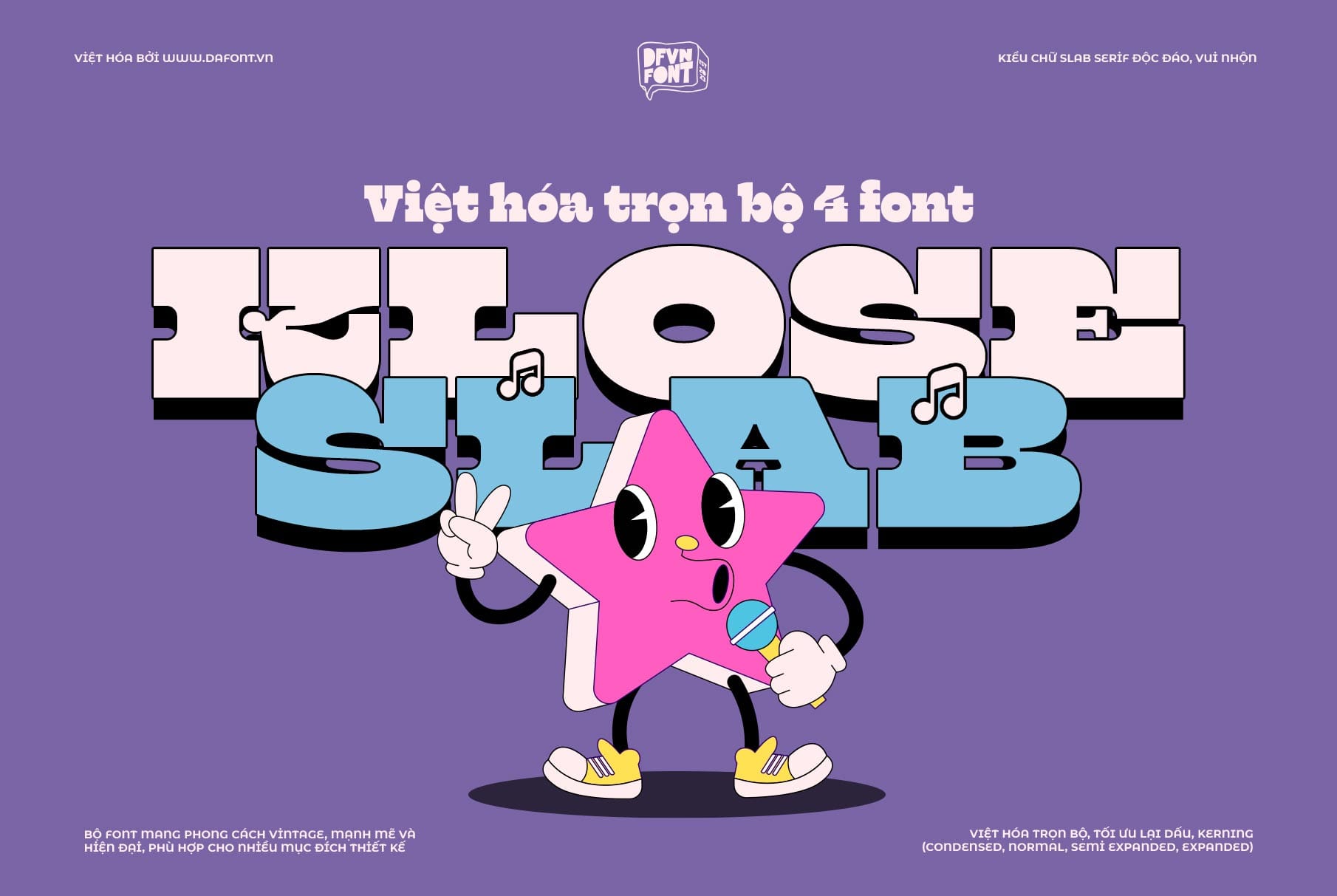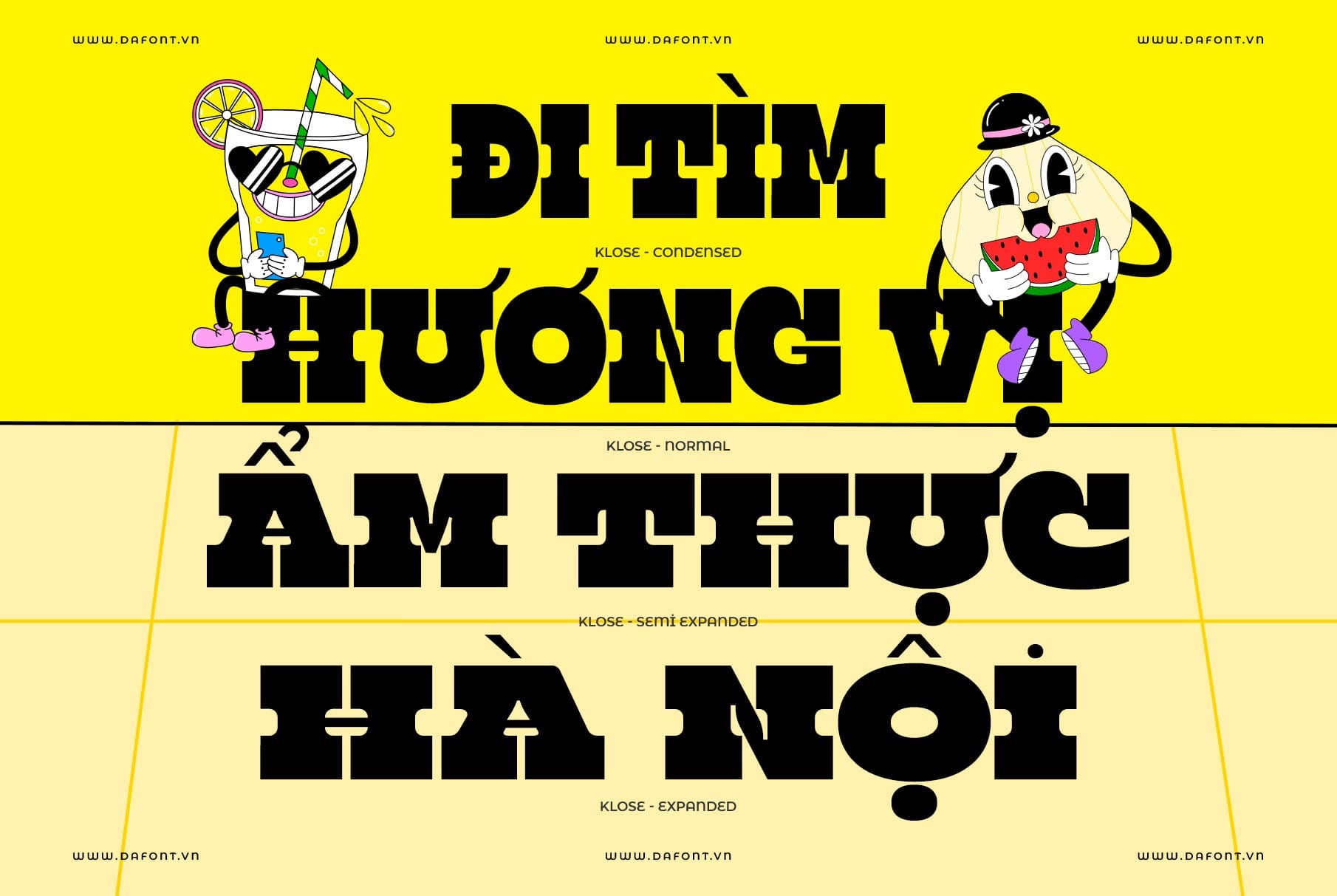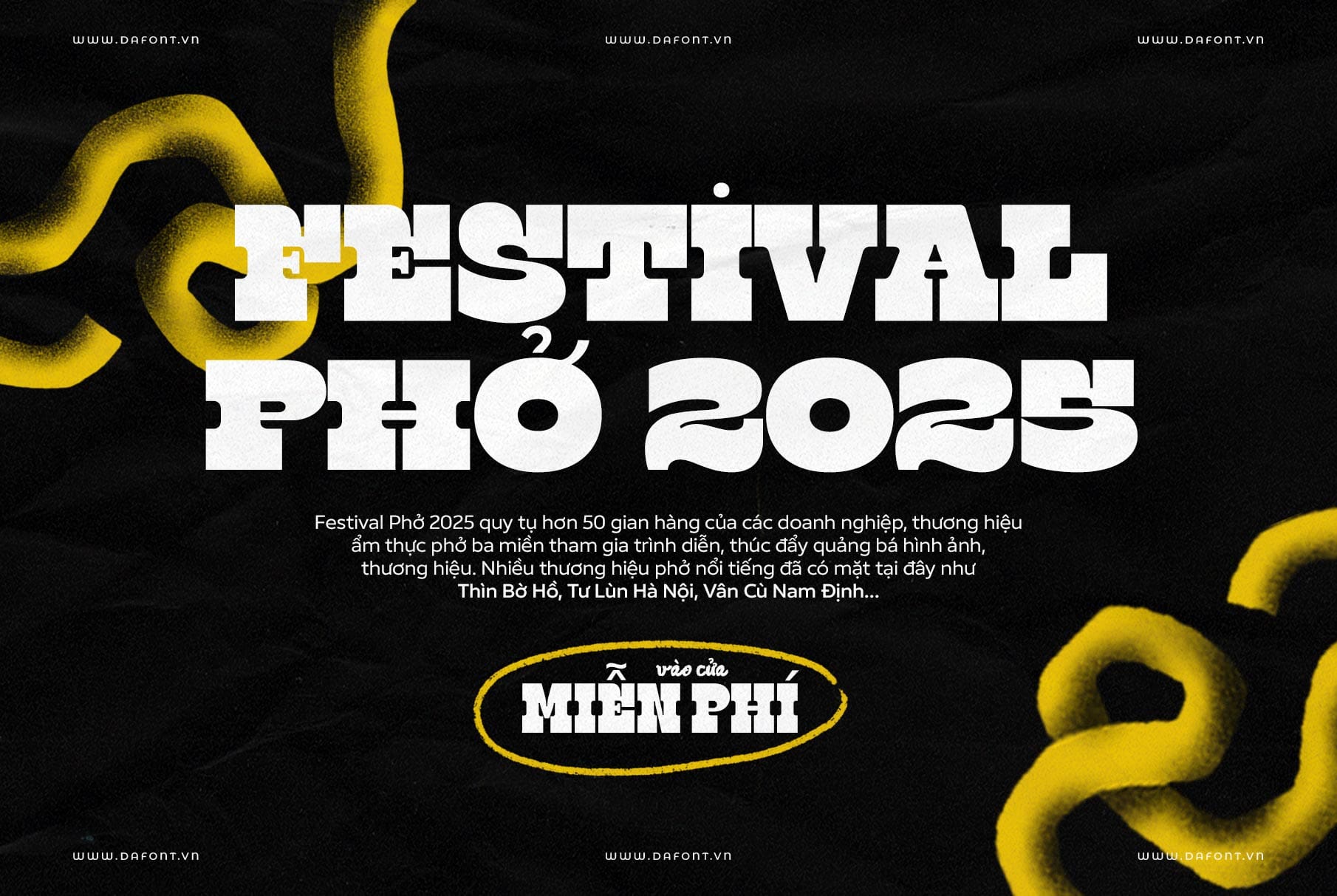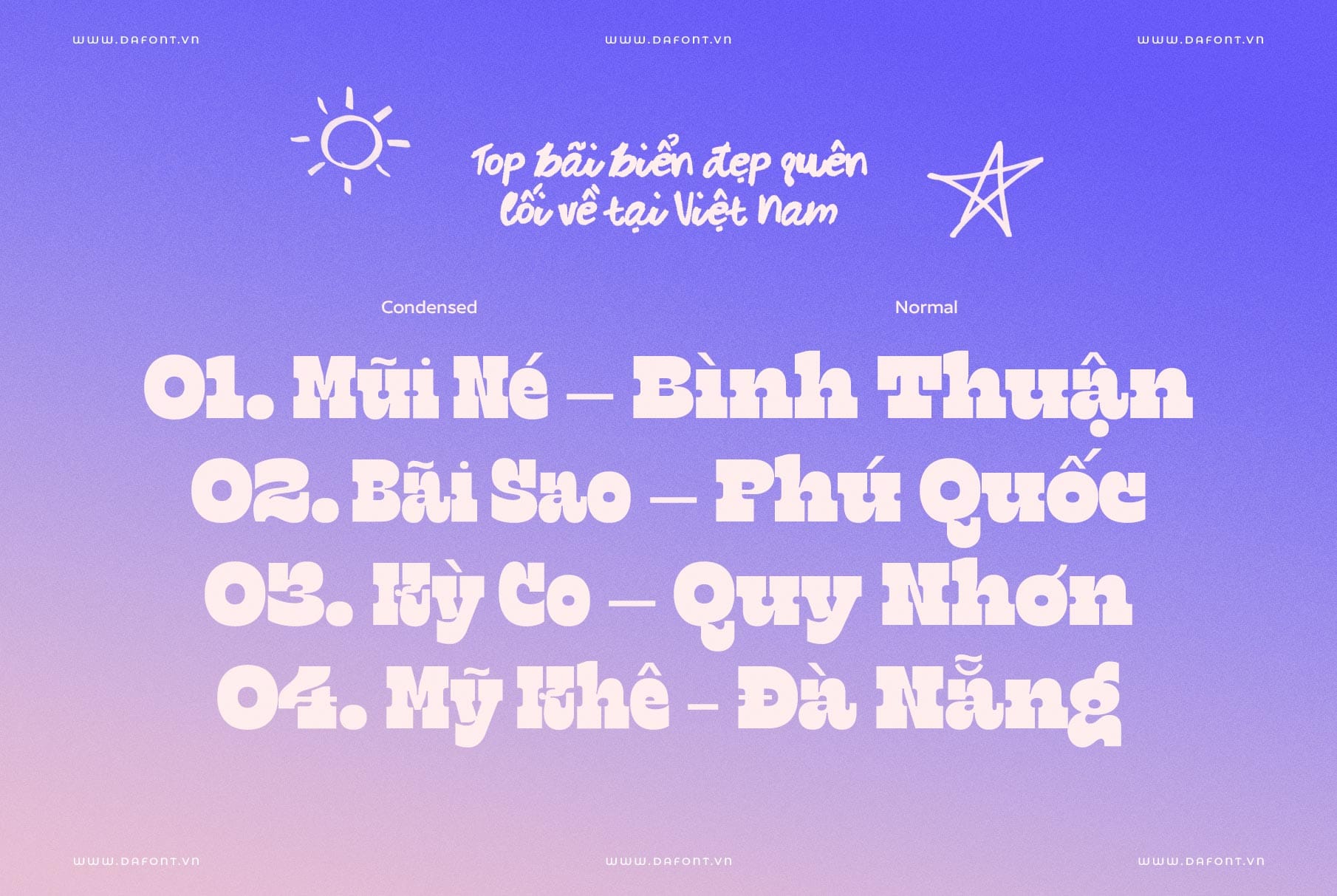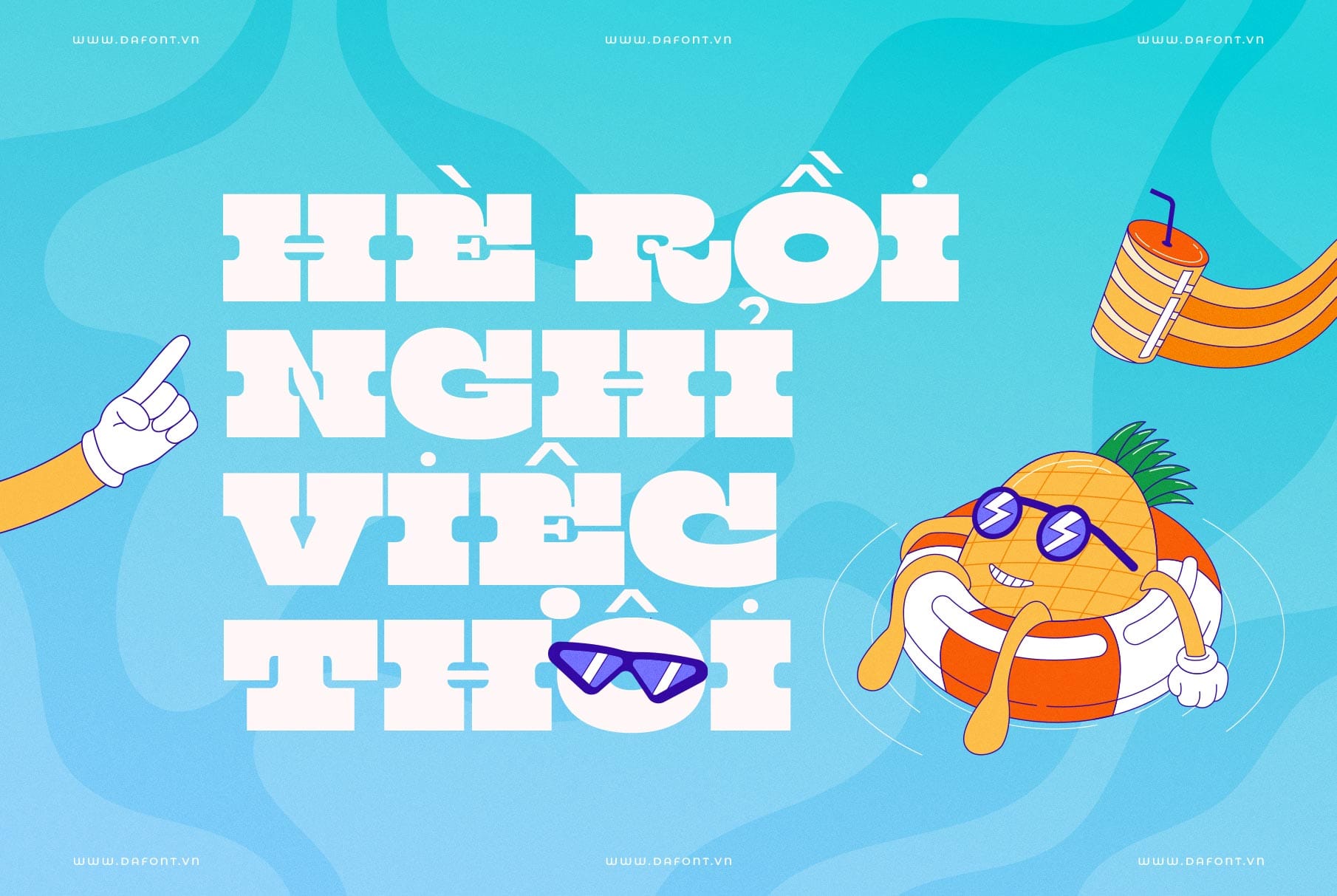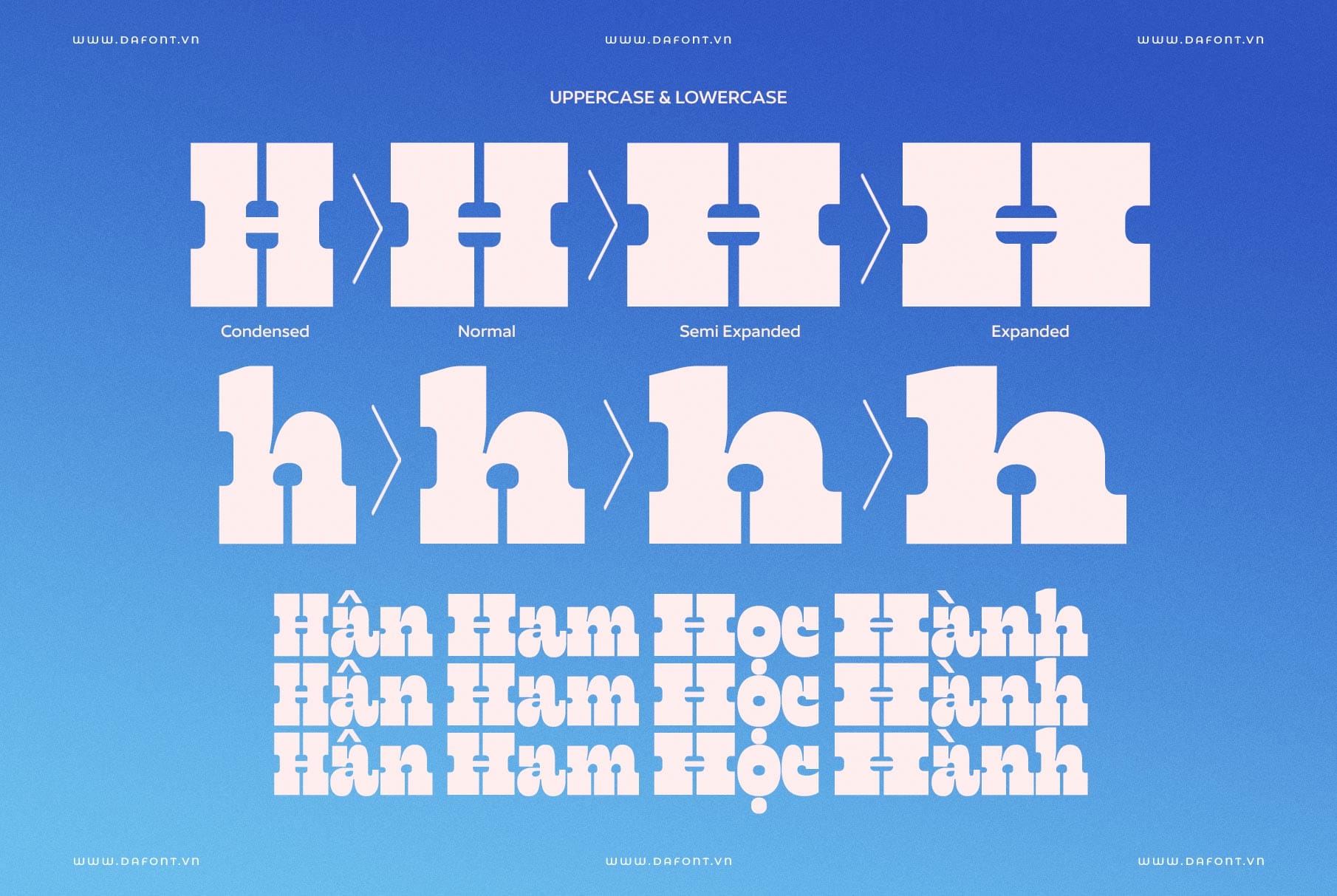
DFVN Klose Slab, một typeface độc đáo mang đến sự cân bằng hoàn hảo giữa vẻ đẹp cổ điển và tính ứng dụng ngày nay. Bộ font lý tưởng cho tiêu đề, logo, poster và các ứng dụng hiển thị cỡ lớn nhờ nét chữ đậm, góc cắt mạnh mẽ mang phong cách vintage-modern.
Klose Slab vừa có nét cổ điển vintage nhưng vẫn mang hơi hướng hiện đại, giúp các thiết kế trở nên nổi bật và dễ nhìn trong các kích thước lớn. Nhờ dạng slab-serif đậm, font này cũng đảm bảo độ đọc tốt khi in ấn hoặc trình chiếu kỹ thuật số, đồng thời góc cắt rõ ràng giúp tăng cường tính nhận diện thương hiệu.
Điểm nổi bật DFVN Klose Slab
Klose Slab thuộc nhóm slab serif, một loại typeface đặc trưng bởi các nét chữ đậm, vuông vức, mang lại cảm giác mạnh mẽ. Điểm nổi bật của font này nằm ở sự đa dạng về kiểu dáng, bao gồm 4 kiểu Condensed, Normal, Semi Expanded và Expanded.
Với vẻ ngoài ấn tượng và dễ đọc, Klose Slab được ứng dụng rộng rãi trong nhiều lĩnh vực thiết kế:
- Thiết kế logo: Tạo nên những logotype mạnh mẽ, ghi dấu ấn thương hiệu.
- Tiêu đề và văn bản nổi bật: Lý tưởng cho headlines hoặc displayed text trên ấn phẩm in ấn và kỹ thuật số.
- Thiết kế web và quảng cáo: Mang lại sự hài hòa giữa thẩm mỹ và tính ứng dụng.
Font này dễ dàng kết hợp với các typeface khác như sans-serif hoặc serif, tạo nên sự tương phản hoặc thống nhất độc đáo. Dù bạn làm việc với dự án thương hiệu hay biên tập, Klose Slab đều có thể nâng cao chất lượng thiết kế của bạn.
Kết luận
Với thiết kế slab-serif đậm nét, độ linh hoạt cao và Việt hóa tỉ mỉ căn chỉnh đồng đều từng dấu, Klose Slab là lựa chọn hoàn hảo cho các dự án cần điểm nhấn mạnh mẽ trên tiêu đề, logo và hiển thị lớn. Việc kết hợp với các font sans-serif mảnh càng tô đậm hiệu quả thị giác, giúp thông điệp được truyền tải rõ ràng và thu hút hơn.